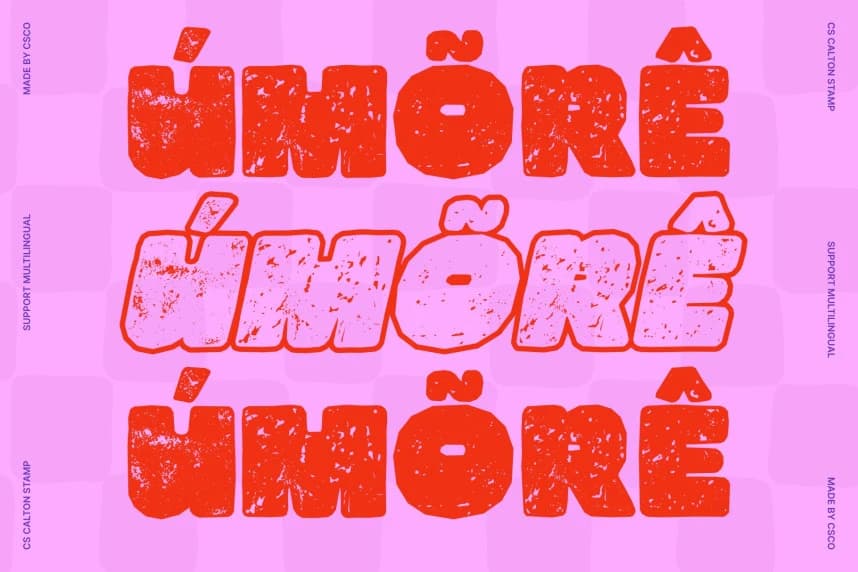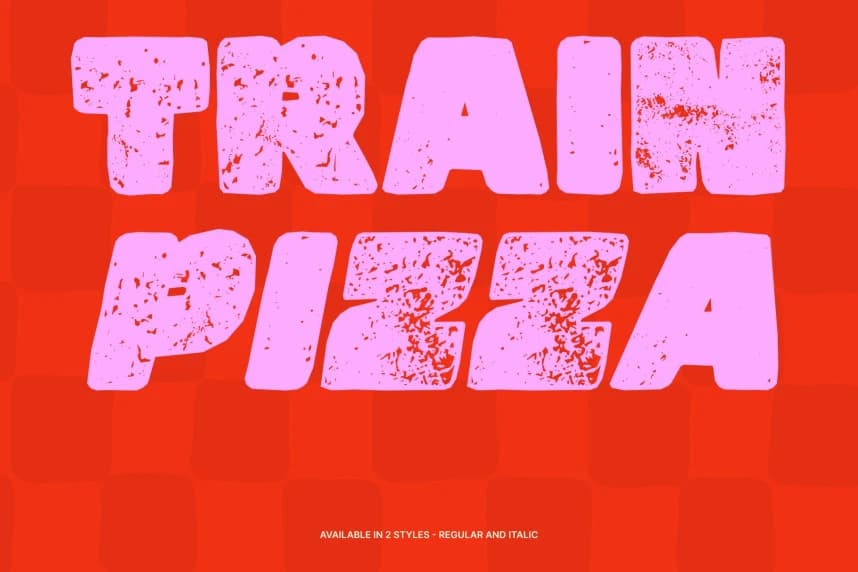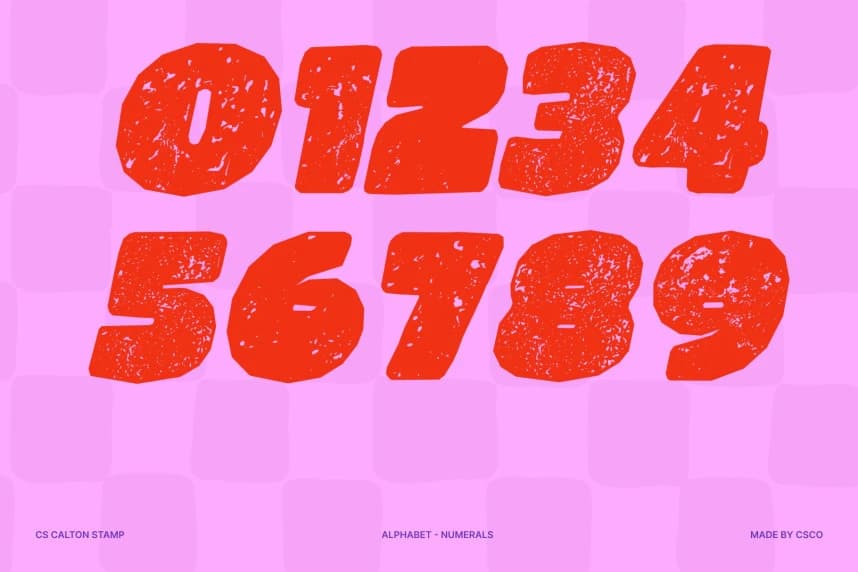
CS Calton Stamp Font
CS Calton Stamp Font – Vintage Damga Karakterli Güçlü Etki. Dokuya sahip karakteriyle gösterişli bir Sans Serif fontu. Bu, dikkat çekmek üzere tasarlanmış kalın bir gösterim Sans Serif fontudur.
CS Calton Stamp Font – Vintage pul karakteriyle güçlü etki, dokulu kişiliğe sahip Gösterişli Sans Serif. Bu, dikkat çekmek için tasarlanmış kalın bir gösterişli sans serif yazı tipidir.